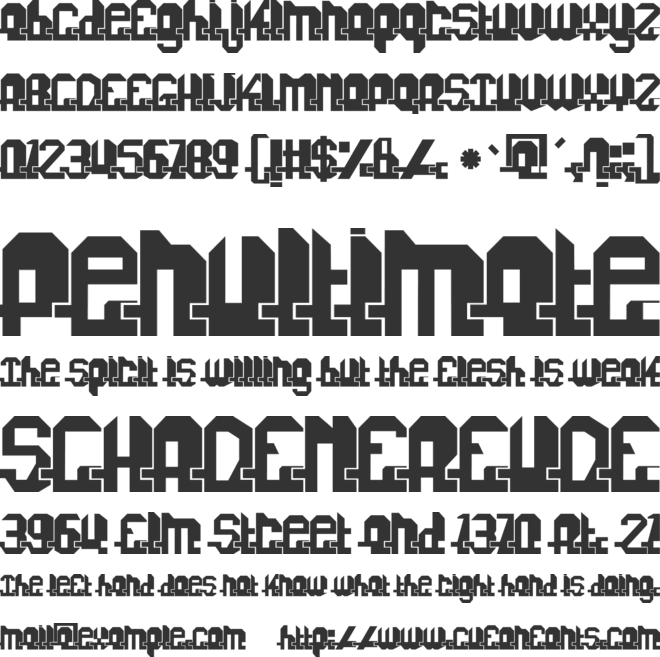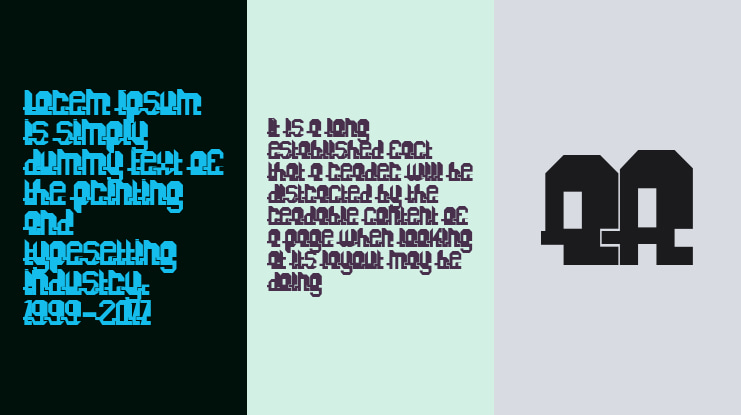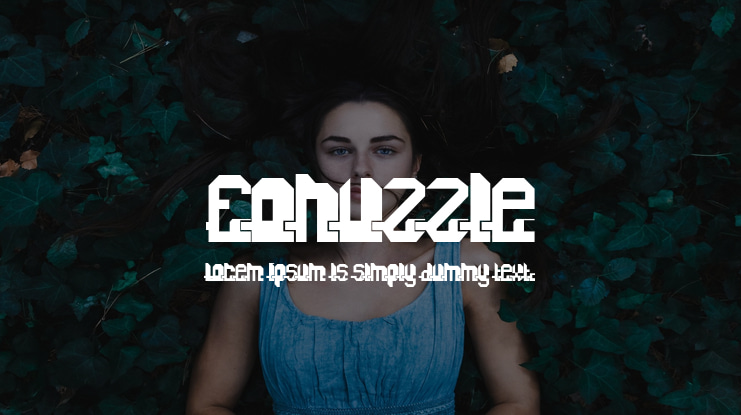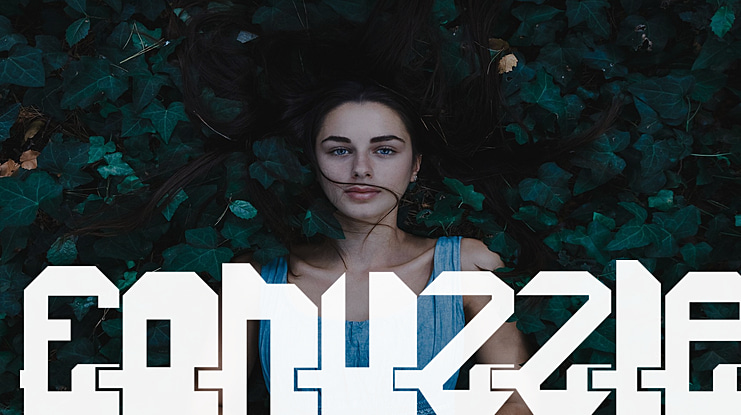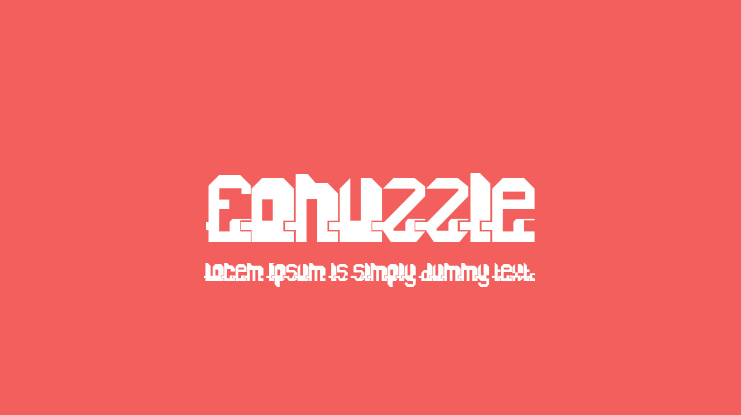
Fonuzzle Font
Una tipografía de carácter totalmente experimental. Fue para mi clase de tipografía en mi última entrega de parcial.
Como en los parciales anteriores me dediqué a realizar tipografías comunes, tuve la curiosidad de crear una tipografía totalmente diferente y en general algo que nunca había visto: que toda la tipografía estuviera conectada de algún modo.
Mis primeras ideas fueron hacerla en cursiva, pero iba a batallar con el ductus base, así que como buen amante de los videojuegos se me vino a la mente esto, creada por trazos rectos.
Ésta tipografía esta conectada totalmente, desde las mayúsculas con las minúsculas, y estas mismas con los signos y viceversa, aunque cabe mencionar que hay signos que no tienen esta conexión, pero la mayoría la tiene.